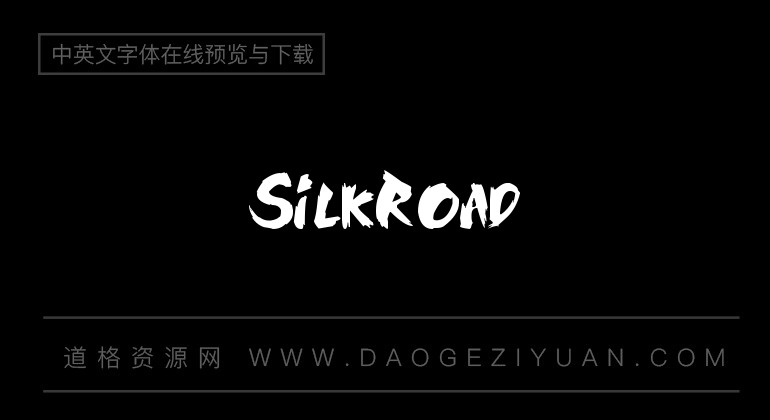
SilkRoad 字体是由设计师兼字体制作人阿喜(Hans van Maanen)创建的一种精美、优雅的字体。该字体是以丝绸之路为灵感而设计的,因此命名为 SilkRoad。 该字体的特点是结合了传统的东方和现代的西方设计元素,形成了一种独特的风格。它的字形优美流畅,具有很高的识别度。同时,它还包含了多种语言字符,适用于全球范围内的设计需求。 SilkRoad 字体包括了 Regular、Italic、Bold 三种字重和多种 OpenType 特性,例如小型大写字母、下划线字母、分数、标点符号等,可以满足设计师对于字体的各种需求。 总的来说,SilkRoad 字体是一款适用于多种设计场景的字体,包含了东方和西方设计元素的独特融合,让设计师能够实现多样化的创意表达。内容介绍
SilkRoad是一款非常不错的手写艺术字体,具有很好的视觉感,适合于文化类的宣传设计、商业类品牌的广告和产品包装设计以及个性化文字排版等较多场景。